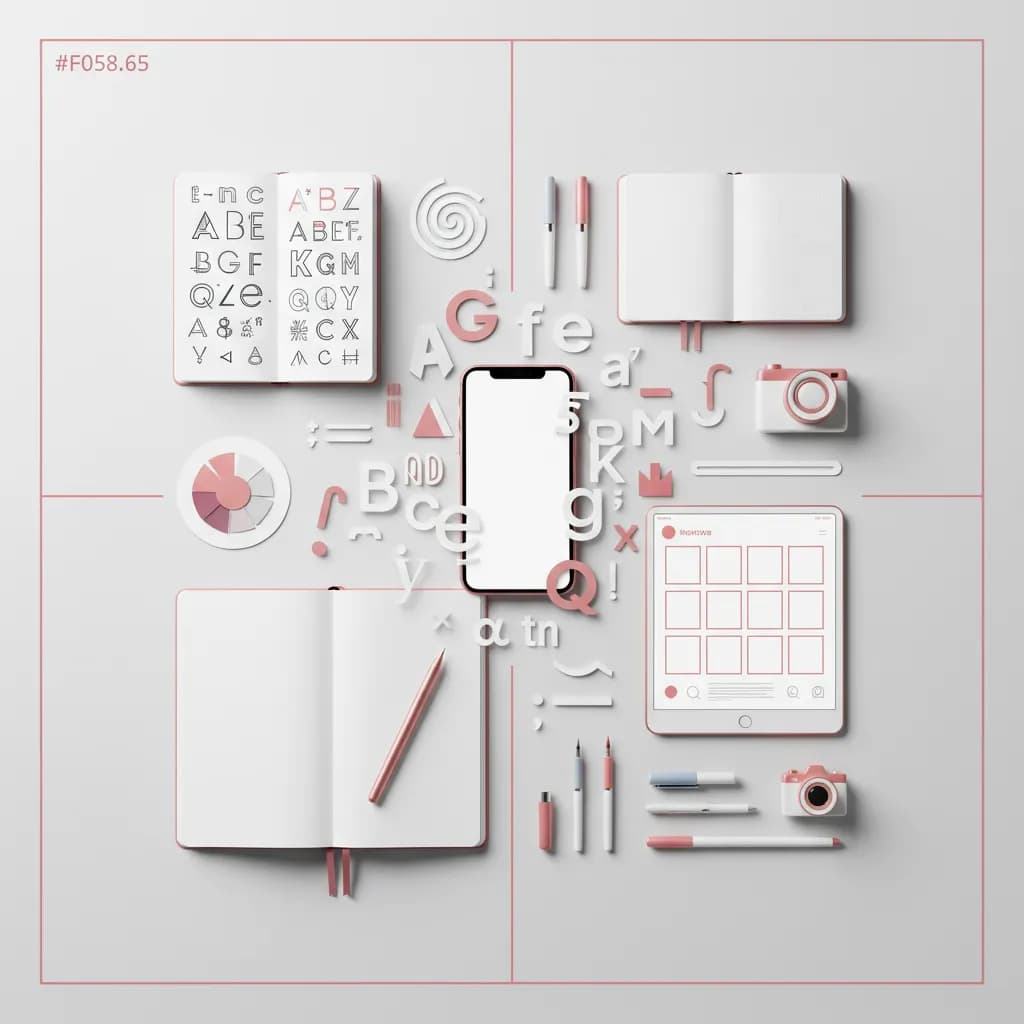
אם אי פעם ניסיתם לגרום לפוסט באינסטגרם להתבלט בים התוכן האינסופי, אתם בוודאי יודעים שהעיצוב החזותי הוא המפתח. בעידן שבו משתמשים גוללים במהירות דרך מאות תמונות ביום, היכולת לעצור את העין תלויה בפרטים הקטנים – ובראש ובראשונה, בבחירת הפונטים הנכונים. העיצוב החזותי עם פונטים באינסטגרם הוא לא רק עניין של אסתטיקה, אלא כלי אסטרטגי שמשפיע על מעורבות, זיהוי מותג וההצלחה הכוללת של התוכן שלכם.
למה זה משנה? כי פונט נכון לא רק מעביר מסר – הוא גם יוצר חוויה רגשית, מחזק את זהות המותג ומגדיל את הסיכוי שהקהל שלכם יעצור, יקרא ויגיב. במדריך זה נלמד כיצד לבחור, לעצב ולשלב פונטים בצורה שתהפוך את הפרופיל שלכם למקצועי ובלתי נשכח.
העיצוב החזותי עם פונטים באינסטגרם הוא יסוד מרכזי בבניית נוכחות דיגיטלית חזקה. בניגוד לפלטפורמות אחרות, אינסטגרם היא פלטפורמה ויזואלית במהותה – משתמשים מגיבים תחילה לעיצוב החזותי, ורק אחר כך לתוכן הכתוב. מחקרים בתחום UX Research מצביעים על כך שאנשים מעבדים מידע ויזואלי פי 60,000 מהר יותר מטקסט רגיל, מה שהופך את הפונטים לכלי תקשורת מיידי.
הסיבה הראשונה היא זיהוי מותג. כאשר אתם בוחרים פונט עקבי לכל התוכן שלכם, אתם יוצרים חתימה ויזואלית שהקהל מזהה מיד. בדיוק כמו שמותגים גדולים משתמשים בצבעים ייחודיים, גם הטיפוגרפיה שלכם הופכת לחלק מהזהות המותגית. לדוגמה, מעצבים רבים משתמשים בפונטים מודרניים ונקיים כדי להעביר תחושת מקצועיות – פונט דיפלומט הוא דוגמה מצוינת לפונט גמיש ודו-לשוני שמתאים לעיצובים דיגיטליים מקצועיים.
הסיבה השנייה היא קריאות ונגישות. פונט שקשה לקריאה יגרום למשתמשים לדלג על הפוסט, גם אם התוכן מעולה. במחקרי חקר צרכנות נמצא שטיפוגרפיה משפיעה על תפיסת ערך המוצר – פונט ברור ומעוצב היטב יכול להגדיל את האמון והמעורבות של הצופים.
נקודות מפתח:לפני שצוללים לעיצוב, חשוב להבין את הקטגוריות העיקריות של פונטים ואת השימושים המתאימים לכל אחד. ההבנה הזו תעזור לכם לקבל החלטות מושכלות ולהימנע מטעויות נפוצות.
1. Sans-Serif – הבחירה המודרנית
פונטים מסוג Sans-Serif (ללא תגיות) הם הבחירה הפופולרית ביותר לעיצוב דיגיטלי. הם נקיים, קלים לקריאה במסכים קטנים ומשדרים תחושה עכשווית ומינימליסטית. במחקרי UX נמצא שפונטים אלו מפחיתים עייפות עיניים ומשפרים קריאות בממשקים דיגיטליים. לדוגמה, פונט אספרסו הוא פונט Sans-Serif דו-לשוני מנוקד שמתאים במיוחד לטקסט רץ בעיצובים דיגיטליים.
2. Serif – האלגנטיות הקלאסית
פונטים מסוג Serif (עם תגיות) משדרים מסורת, יוקרה ואמינות. הם מצוינים לכותרות ולעיצובים שרוצים להעביר תחושה קלאסית או מלומדת. פונטים כאלה מתאימים למותגים בתחומי האופנה, התרבות או המזון היוקרתי. למשל, עבור עיצובים עם נופך מסורתי, פונט מזרחי מציע אותיות עם נשמה מזרחית וזיכרון שלא יישכח, מתאים במיוחד לכותרות עם אופי תנכ״י וקליגרפי.
3. Script וכתב יד – האישיות והחום
פונטים בסגנון כתב יד מוסיפים נגיעה אישית ואנושית. הם מתאימים למותגים שרוצים להעביר קרבה, חום ויצירתיות. עם זאת, חשוב להשתמש בהם במשורה ובגדלים גדולים מספיק כדי לשמור על קריאות. מעצבים רבים משלבים אותם בלוגואים או בציטוטים מיוחדים. למידע נוסף על שילוב נכון, כדאי לקרוא את המדריך לבחירת פונטים של כתב יד.
עכשיו כשהבנתם את היסודות, הגיע הזמן ליישם. הנה תהליך מעשי בחמישה שלבים שיעזור לכם לבחור ולשלב פונטים בצורה מקצועית.
שלב 1: הגדירו את זהות המותג והקהל
התחילו בשאלות יסודיות: מה הערכים המרכזיים של המותג שלכם? האם אתם רוצים להיראות מודרנייים, קלאסיים, משחקיים או רציניים? קהל היעד שלכם – האם הוא צעיר ודיגיטלי, או בוגר ומקצועי? התשובות האלה יכוונו אתכם לקטגוריית הפונטים המתאימה. לדוגמה, מותג טכנולוגי צעיר יתאים לו פונט Sans-Serif נקי, בעוד מותג יוקרה יכול להרשות לעצמו Serif אלגנטי.
שלב 2: בחרו 2-3 פונטים מקסימום
כלל הזהב בטיפוגרפיה: פחות זה יותר. בחרו פונט אחד לכותרות ואחד לטקסט גוף, ולכל היותר שלישי למבטאים מיוחדים. יותר מזה יגרום לעיצוב להיראות מבולגן וחסר מיקוד. וודאו שהפונטים משלימים אחד את השני – למשל, כותרת בולטת עם טקסט גוף עדין. לעיצובים שדורשים גמישות, פונט דיפלומט מציע משקלים מרובים (קל, רגיל, בולט) שמאפשרים היררכיה ברורה בתוך אותה משפחת פונטים.
שלב 3: בדקו קריאות במסכים שונים
לפני שאתם מתחייבים לפונט, בדקו אותו בגדלים שונים ובמכשירים שונים – טלפון, טאבלט, מחשב. פונט שנראה מדהים במסך גדול עלול להיות בלתי קריא בסטורי של אינסטגרם. הקפידו על גודל מינימלי של 14-16px לטקסט גוף ו-24-32px לכותרות. מרחק בין שורות (line-height) של 1.5-1.7 משפר משמעותית את הקריאות.
שלב 4: יצרו היררכיה ויזואלית ברורה
השתמשו בגדלים, משקלים וצבעים כדי ליצור היררכיה. הכותרת צריכה להיות הבולטת ביותר, אחריה כותרות משנה, ולבסוף טקסט גוף. הניגודיות הזו מנחה את העין של הצופה ומקלה על צריכת התוכן. טכניקה נפוצה: כותרת בגודל 32px ומשקל כבד, כותרת משנה ב-24px רגיל, טקסט גוף ב-16px רגיל.
שלב 5: שמרו על עקביות לאורך זמן
ברגע שבחרתם בפונטים, הקפידו להשתמש בהם באופן עקבי בכל הפוסטים. עקביות בונה זיהוי מותג ומקלה על הקהל לזהות את התוכן שלכם בפיד. צרו מדריך סגנון פשוט עם הפונטים, הגדלים והצבעים שבחרתם, והקפידו לעקוב אחריו.
גם מעצבים מנוסים נופלים לעיתים למלכודות טיפוגרפיות. הכרת הטעויות הנפוצות תעזור לכם לחסוך זמן ותסכול.
טעות 1: שימוש ביותר מדי פונטים בפוסט אחד
כאשר משלבים 4-5 פונטים שונים בפוסט אחד, התוצאה נראית חובבנית ומבולגנת. הפתרון: הגבילו את עצמכם ל-2 פונטים בלבד – אחד לכותרות ואחד לטקסט. אם אתם זקוקים לווריאציה, השתמשו במשקלים שונים של אותו פונט במקום להוסיף פונט נוסף.
טעות 2: פונטים דקורטיביים לטקסט ארוך
פונטים מעוטרים או מסוגננים מדי נראים מדהים בכותרות קצרות, אבל הופכים לבלתי קריאים בטקסט ארוך. למשל, פונטים גראנג׳ או קליגרפיים מורכבים מתאימים למשפט אחד בלבד. לטקסט רץ, בחרו תמיד פונט פשוט וברור. פונט תפארת, למשל, מתאים גם לטקסט רץ וגם לכותרות הודות לעיצובו הקליגרפי האלגנטי אך הקריא.
טעות 3: התעלמות מניגודיות צבעים
טקסט צהוב על רקע לבן, או טקסט אפור בהיר על רקע אפור – אלו דוגמאות לניגודיות גרועה שהורסת קריאות. וודאו שיש הבדל ברור בין צבע הטקסט לרקע. כלל אצבע: יחס ניגודיות של לפחות 4.5:1 לטקסט רגיל ו-3:1 לטקסט גדול. אתם יכולים לבדוק את זה באתרים כמו Wikipedia – Contrast Ratio.
טעות 4: חוסר עקביות בין פוסטים
שימוש בפונט שונה בכל פוסט מבלבל את הקהל ומונע בניית זהות מותגית. הפתרון: צרו תבנית עיצובית קבועה עם אותם פונטים, צבעים ומבנה. רק התוכן משתנה, העיצוב נשאר עקבי. זה חוסך זמן ומחזק את המיתוג.
כדי ליישם את העקרונות שלמדנו, תזדקקו לכלים נכונים. הנה המשאבים המומלצים ביותר לעבודה עם פונטים באינסטגרם.
כלי עיצוב גרפי
Canva ו-Adobe Express הם הפלטפורמות הפופולריות ביותר ליצירת פוסטים לאינסטגרם. שניהם מציעים תבניות מוכנות, ספריות פונטים נרחבות ואפשרויות התאמה אישית. ל-Canva יש אפילו גדלים מוכנים לפורמטים שונים של אינסטגרם (פיד, סטורי, רילס). למעצבים מתקדמים, Adobe Photoshop ו-Illustrator מספקים שליטה מלאה יותר.
ספריות פונטים
Google Fonts מציעה מאות פונטים חינמיים לשימוש מסחרי, עם תמיכה במגוון שפות. עבור פונטים עבריים מקצועיים ויחודיים, כדאי לחקור אפשרויות ייעודיות. לדוגמה, למי שמחפש פונט עם אופי מיוחד, פונט בלון מציע סגנון נוסטלגי וקופצני המתאים לתוכן משחקי ומהנה.
אפליקציות לעריכת טקסט בסטוריז
אפליקציות כמו Unfold ו-StoryArt מתמחות בתבניות לסטוריז עם טיפוגרפיה יפה. הן מציעות סגנונות מוכנים שניתן להתאים בקלות. חלקן כוללות גם אפשרויות אנימציה לטקסט, מה שמוסיף דינמיות לתוכן.
כלי בדיקת נגישות וקריאות
לפני פרסום, כדאי לבדוק את הניגודיות והקריאות. כלים מקוונים יכולים לבדוק אם העיצוב שלכם עומד בתקני נגישות בינלאומיים. זה לא רק עוזר לאנשים עם לקויות ראייה, אלא משפר את החוויה לכל המשתמשים.
התחילו בהגדרת הערכים והאישיות של המותג – האם הוא מודרני או מסורתי, רציני או משחקי, מינימליסטי או עשיר? בחרו קטגוריית פונט שמשקפת את התכונות האלה: Sans-Serif למודרניות, Serif לקלאסיות, Script לאישיות. בדקו את הפונט על תוכן אמיתי ובמכשירים שונים לפני החלטה סופית.
הכלל המקובל הוא מקסימום 2-3 פונטים: אחד לכותרות, אחד לטקסט גוף, ולכל היותר שלישי למבטאים מיוחדים. שימוש ביותר פונטים יוצר בלאגן ויזואלי ומפריע לקריאות. חלופה טובה היא להשתמש בפונט אחד עם משקלים שונים (רגיל, בולד, קל) ליצירת היררכיה.
לטקסט גוף, השתמשו בגודל מינימלי של 14-16px כדי להבטיח קריאות במסכי סמארטפון. לכותרות, 24-32px הוא טווח טוב. זכרו שהקריאות תלויה גם בצבע, ניגודיות ומשקל הפונט – פונט דק יזדקק לגודל גדול יותר מפונט כבד. תמיד בדקו את העיצוב במכשיר נייד לפני פרסום.
העיצוב החזותי עם פונטים באינסטגרם הוא אחד הכלים החזקים ביותר בארסנל שלכם ליצירת תוכן בולט ומקצועי. כפי שראינו, בחירת הפונט הנכון משפיעה על זיהוי המותג, קריאות, מעורבות ותפיסת האיכות של התוכן שלכם. השקעה בהבנת העקרונות הטיפוגרפיים והימנעות מטעויות נפוצות תחסוך לכם זמן רב ותשפר משמעותית את התוצאות.
הנקודות המרכזיות לזכור: הגבילו את עצמכם ל-2 פונטים בלבד, שמרו על עקביות בכל הפוסטים, וודאו קריאות במכשירים שונים, ויצרו היררכיה ברורה. פונטים באינסטגרם אינם רק אלמנט עיצובי – הם חלק אינטגרלי מהסיפור והחוויה שאתם מציעים לקהל שלכם.